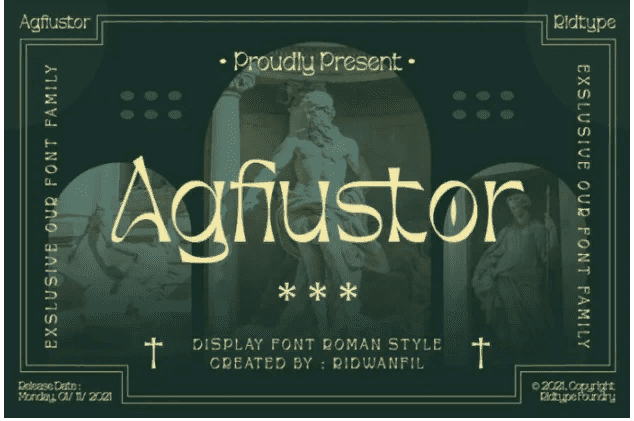
Название: Agfiustor Font (2021)
Agfiustor вдохновлен языком и Римской империей, которая правила несколько веков назад.
После создания Колизея как реликвии, этот шрифт также был создан в честь и в знак признания того, что в то время существовала империя, которая контролировала почти половину населения Земли. Благодаря этому шрифт agfiustor придает каждой букве уникальность, а также имеет несколько чередований и лигатур, благодаря которым шрифт agfiustor выглядит элегантно в любом месте.
Этот шрифт также лучше всего подходит для использования в малых и больших проектах, таких как: логотипы на заказ, брендинг проектов, дизайн упаковки, реклама, печать проектов, дизайн футболок, иллюстрации абстрактного искусства и многое другое, что подходит для использования этого шрифт